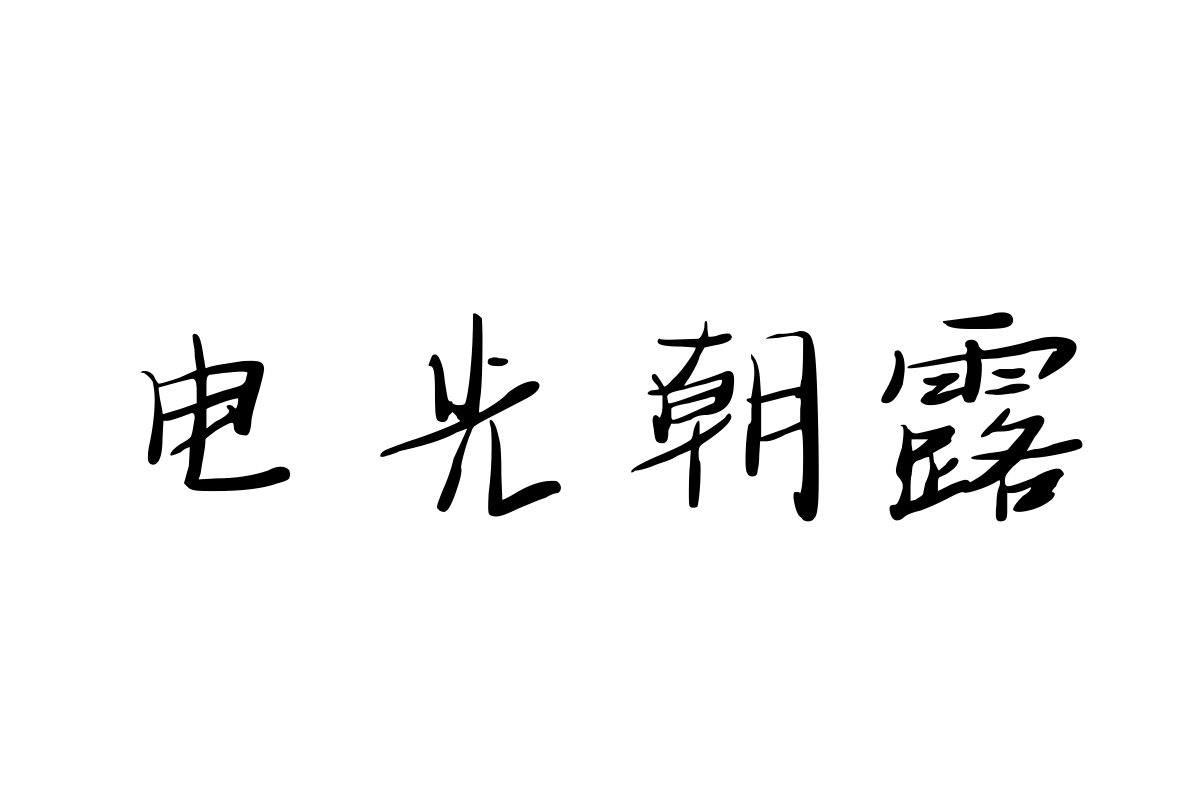
三极风华雪月诗字体是一款具有独特艺术风格的中文字体,由设计师精心打造。这款字体以其独特的字形结构和丰富的变化性而受到广泛欢迎。
三极风华雪月诗字体的特点如下:
1. 字形结构:该字体采用了传统的汉字书写方式,笔画流畅自然,字形结构紧凑而富有美感。同时,字体中还融入了一些现代元素,使得整体风格更加时尚、新颖。
3. 字重感:该字体的字重感较强,使得每个字都显得饱满而有力。这使得读者在阅读时能够更好地感受到文字的内涵和情感。
总之,三极风华雪月诗字体是一款具有独特艺术风格的中文字体,适合用于各种设计项目。